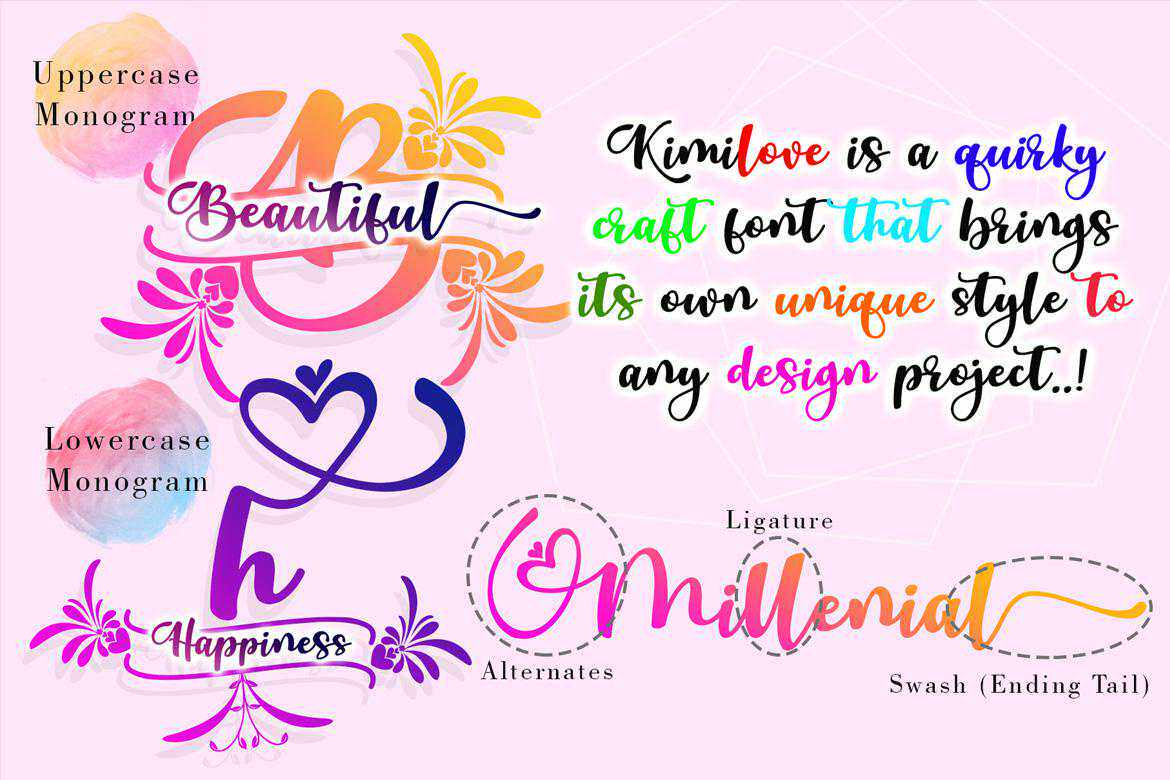
Kimilove感觉到了相当的伤害和宽容。这个字体是经过编码的,这意味着你可以访问字形和Swashease!它的特点是基线、平滑线条、华丽图案和眩晕交替。爱上Kimilove的令人信服的多功能风格,并将其用于创造美丽的婚礼活力、美丽的舞台艺术、吸引眼球的社交主题等等!Kimilove感觉到了相当的伤害和宽容。这个字体是经过编码的,这意味着你可以访问字形和Swashease!它的特点是基线、平滑线条、华丽图案和眩晕交替。爱上Kimilove的令人信服的多功能风格,并将其用于创造美丽的婚礼活力、美丽的舞台艺术、吸引眼球的社交主题等等!